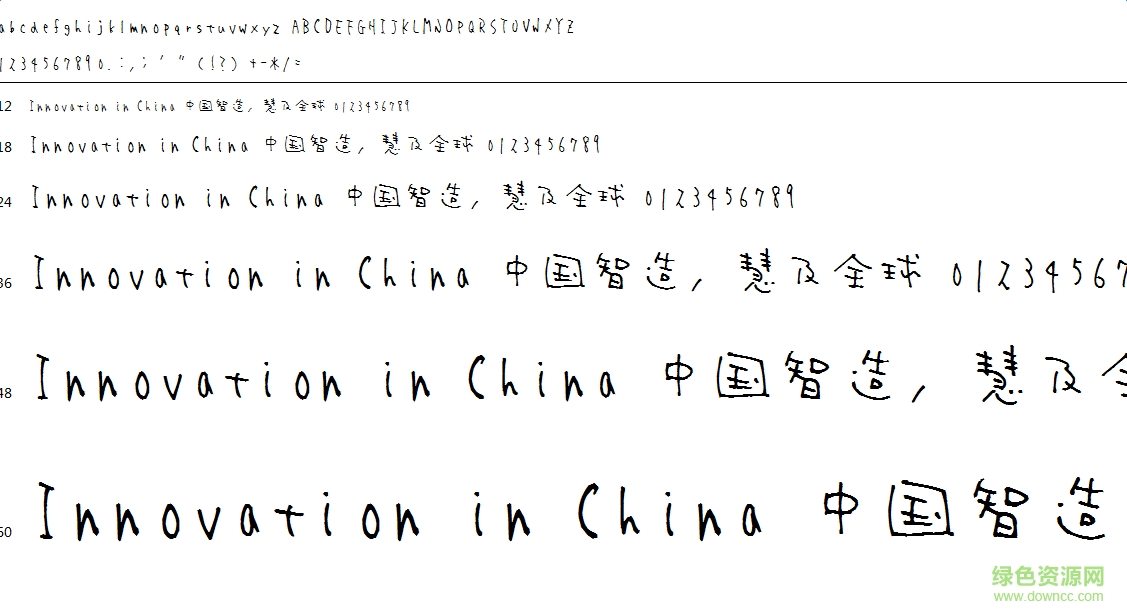
日系手寫(xiě)字體
日系手寫(xiě)風(fēng)字體是一款日系藝術(shù)創(chuàng)意風(fēng)格字體軟件,日系手寫(xiě)體筆畫(huà)隨意卻獨(dú)有一番韻味,非常有創(chuàng)意,整體效果比較搞怪,十分有趣,還有更多好看字體歡迎到綠色資源網(wǎng)下載使用!
日系手寫(xiě)風(fēng)字體